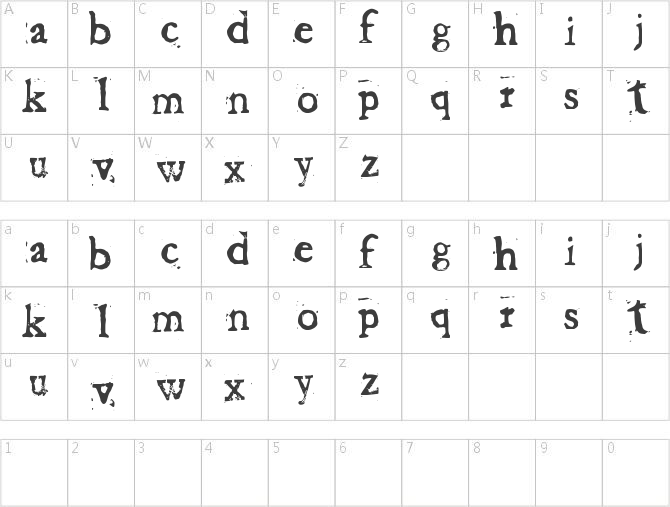
Baketvalley-Old-Face 詳情頁
Baketvalley-Old-Face字體字庫是一款讓人賞心悅目、百看不厭的英文字體,適合各類廣告和產(chǎn)品包裝設(shè)計(jì)應(yīng)用,字體大小0.04MB,格式為ttf字體,上傳用戶是九醬,作者/版權(quán)方為未知